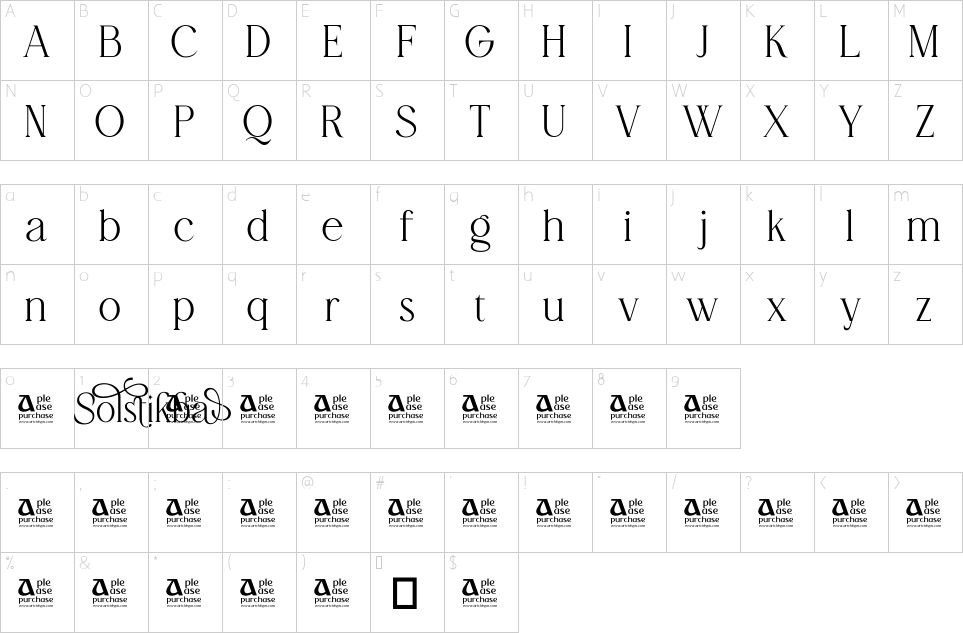
A Solstikba é uma fonte exclusiva para uso pessoal que pode ser baixada tanto no Windows quanto na Mac, com seu design cuidadosamente concebido pela Artchitype Studio. Esta fonte é um presente gratuito de alta qualidade para quem busca dar um toque único e distinto a suas criações digitais. Desde o risco da sua letra até o equilíbrio da tipografia em várias medidas, a Solstikba oferece uma variedade de opções que podem ser usadas tanto no design gráfico quanto na publicidade ou design editorial. Com seu download fácil e conveniente, você pode experimentar a liberdade de criar sem limite, utilizando esta fonte incrivelmente versátil em seus projetos digitais.